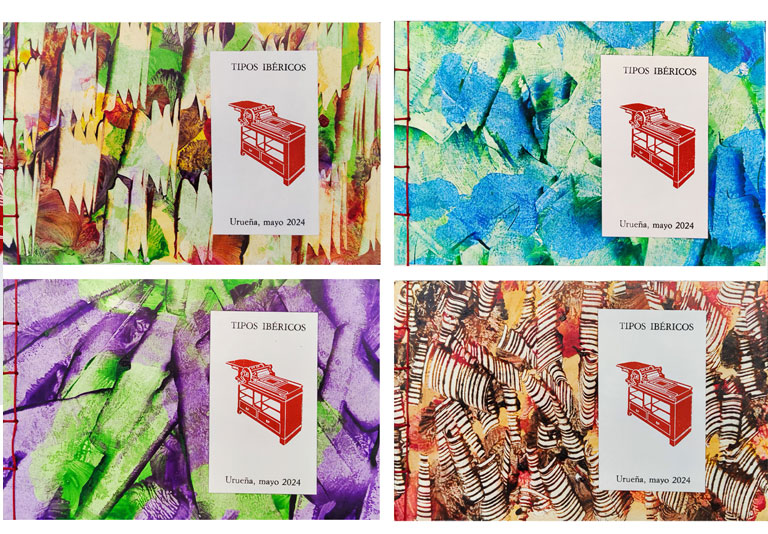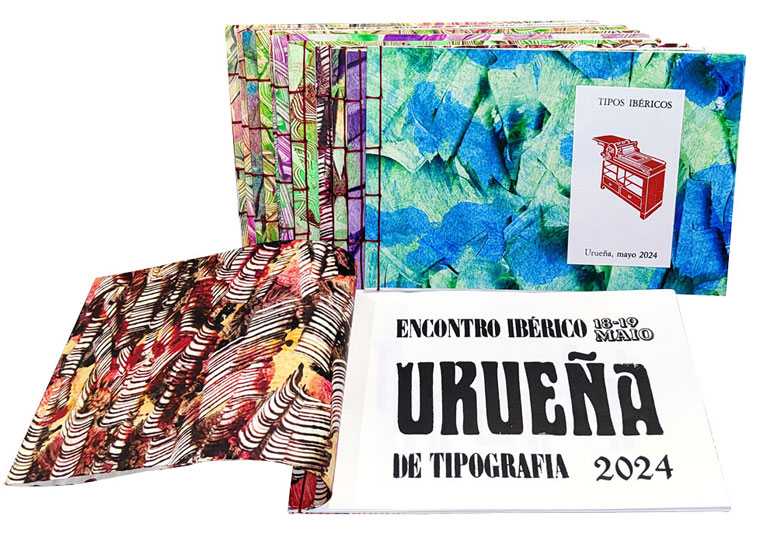
O primeiro trabalho coletivo consistiu na criação de um postal por cada participante, que seria posteriormente encadernado em um pequeno volume. Cada participante seguiu o briefing, contribuindo com uma peça única. O resultado apresentou uma ampla gama de abordagens à prática contemporânea da tipografia. Alguns trabalhos foram inspirados no nome do encontro, “Tipos Ibéricos”, e na geografia do local onde o evento ocorreu.
O contexto individual de cada participante também influenciou a natureza do trabalho produzido, incluindo o relato da viagem e a duração do trajeto até Urueña. Por exemplo, um dos projetos destacou uma abordagem expressiva, que celebra o processo através de ornamentos em vez de tipografia, criando uma composição mais expressiva do que comunicativa.
El primer trabajo colectivo consistió en que cada participante creara una postal, que luego sería encuadernada en un pequeño volumen. Cada participante siguió el encargo, aportando una pieza única. El resultado presentó una amplia gama de enfoques para la práctica contemporánea de la tipografía. Algunas obras se inspiraron en el nombre del encuentro, “Tipos Ibéricos”, y en la geografía del lugar donde se desarrolló el evento.
El contexto individual de cada participante también influyó en la naturaleza del trabajo realizado, incluido el informe de viaje y la duración del viaje a Urueña. Por ejemplo, uno de los proyectos destacó un enfoque expresivo, que celebra el proceso a través del ornamento en lugar de la tipografía, creando una composición que es más expresiva que comunicativa.